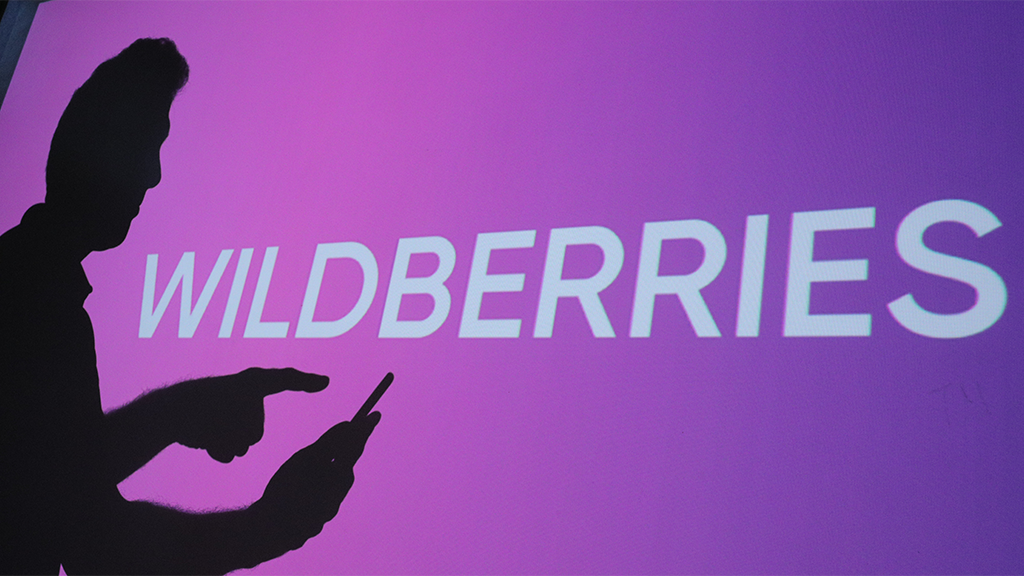
Идеальный шрифт для сайта Вайлдберриз: советы от профессионалов
Вы хотите создать уникальный дизайн сайта в стиле Вайлдберриз? Одним из важных аспектов является выбор подходящего шрифта. В данной статье мы расскажем о том, как выбрать идеальный шрифт, который подчеркнет стиль Вайлдберриз и создаст гармоничную атмосферу на вашем сайте.
Исследуйте стиль Вайлдберриз и определите, какой шрифт будет ему соответствовать. Например, если Вайлдберриз - это стиль ретро, то подходящим шрифтом может быть винтажный или рукописный шрифт.
Учитывайте читаемость. Независимо от стиля Вайлдберриз, шрифт должен быть читабельным и понятным для ваших посетителей.
Подумайте о сочетаемости шрифта с другими элементами дизайна сайта. Шрифт должен гармонировать с цветами, фонами, изображениями и другими элементами.
Изучите примеры успешных сайтов в стиле Вайлдберриз и обратите внимание на то, какие шрифты они используют. Это может быть отличным источником вдохновения и поможет вам выбрать подходящий шрифт для своего проекта.
Протестируйте выбранный шрифт на разных устройствах и браузерах. Убедитесь, что шрифт отображается корректно и выглядит хорошо как на компьютере, так и на мобильных устройствах.
Не бойтесь экспериментировать. Вайлдберриз - это стиль, который позволяет выразить свою индивидуальность и оригинальность. Попробуйте нестандартные шрифты и создайте уникальный дизайн вашего сайта.
Обратите внимание на детали. Какие дополнительные настройки и стили можно применить к выбранному шрифту, чтобы добавить ему больше выразительности?
Слушайте свои интуицию и внутренний голос. В конечном итоге, вы должны быть довольны выбранным шрифтом и верить, что он отражает то, что вы хотите сообщить через свой сайт.
Не забывайте об использовании шрифтовых иконок. Это может быть отличным способом добавить дополнительные элементы дизайна и усилить стиль Вайлдберриз.
Просмотрите шрифты, предлагаемые различными онлайн-сервисами и платформами. Так вы можете найти шрифты, специально разработанные для стилей, похожих на Вайлдберриз, и испытать их бесплатно.